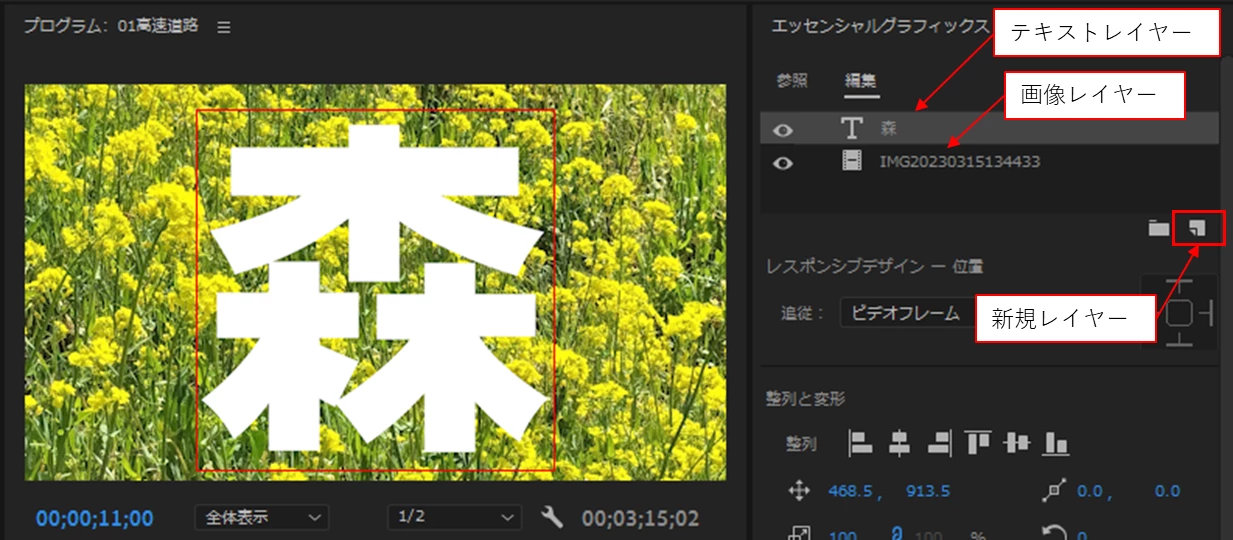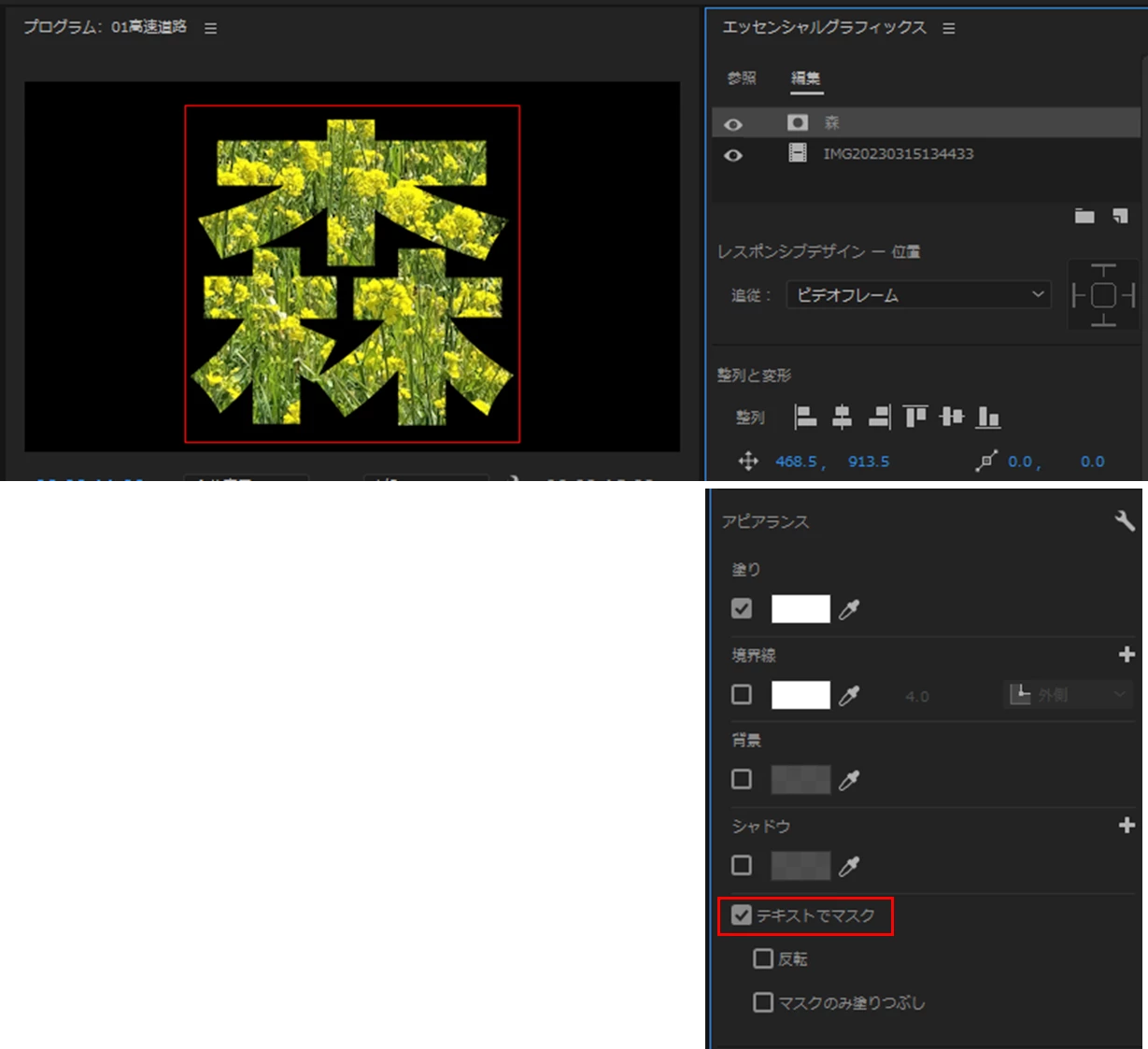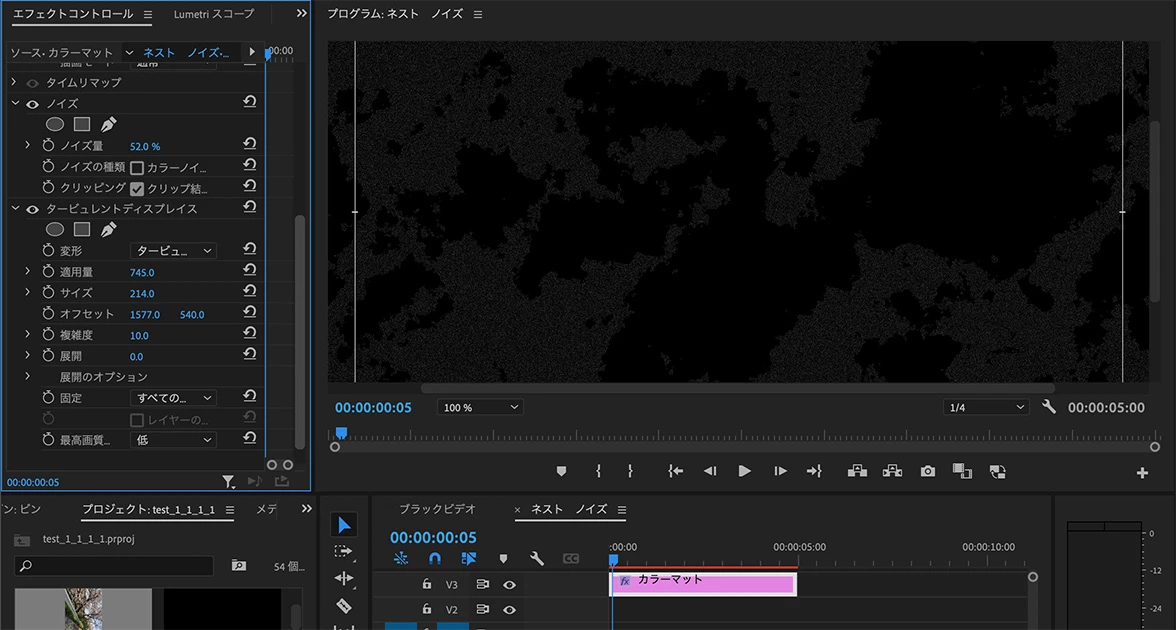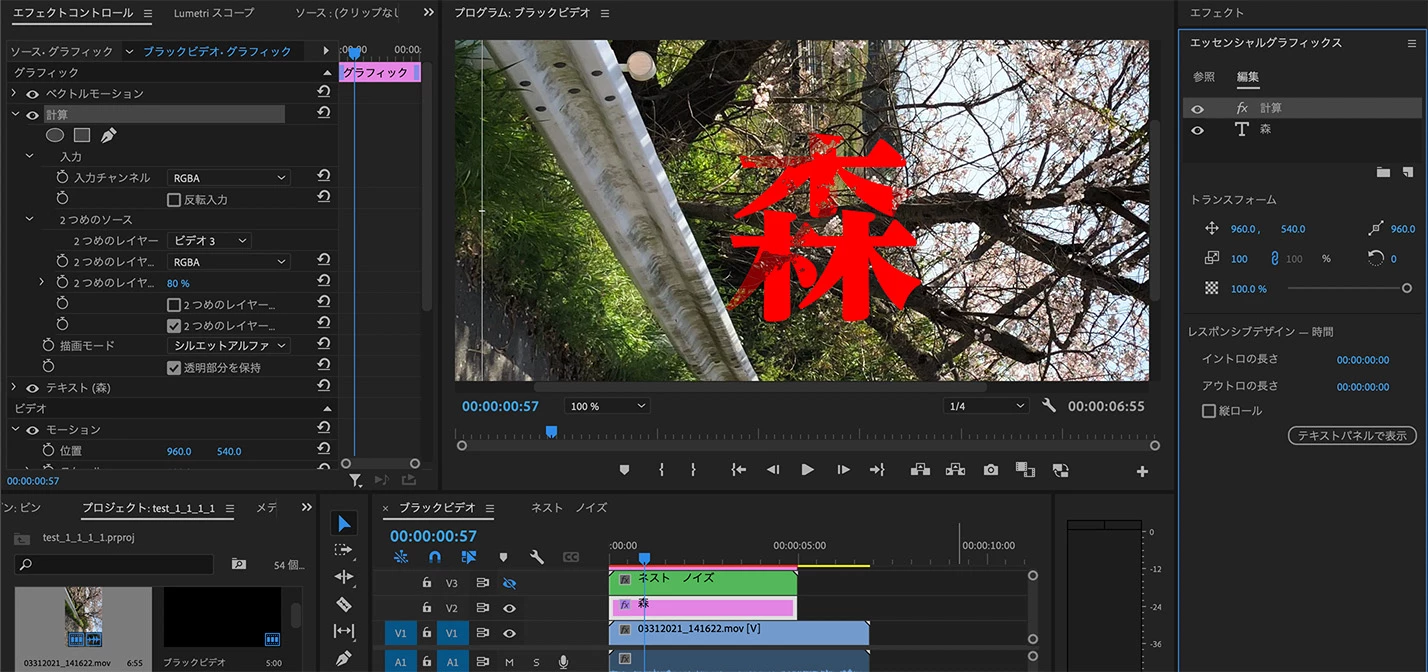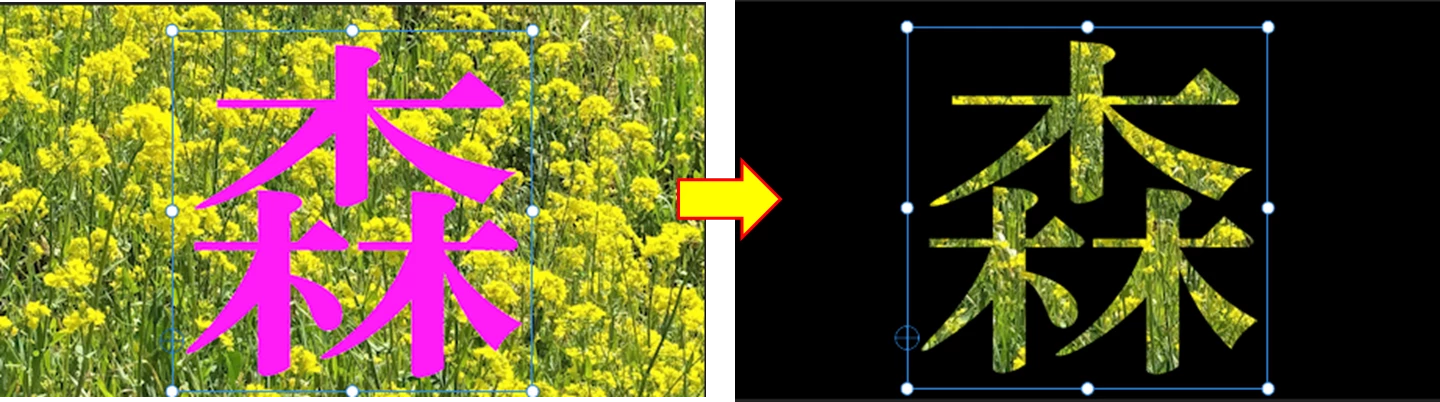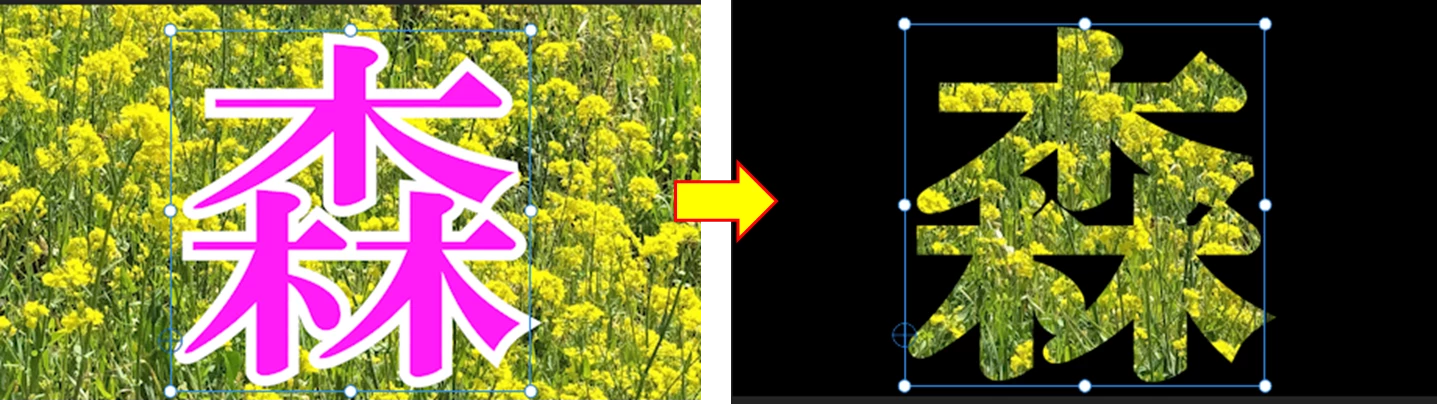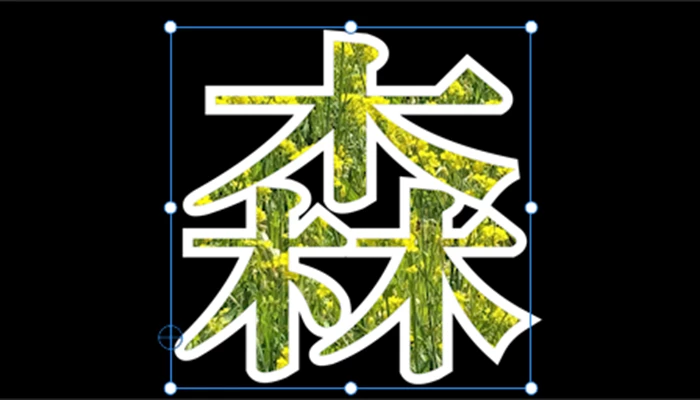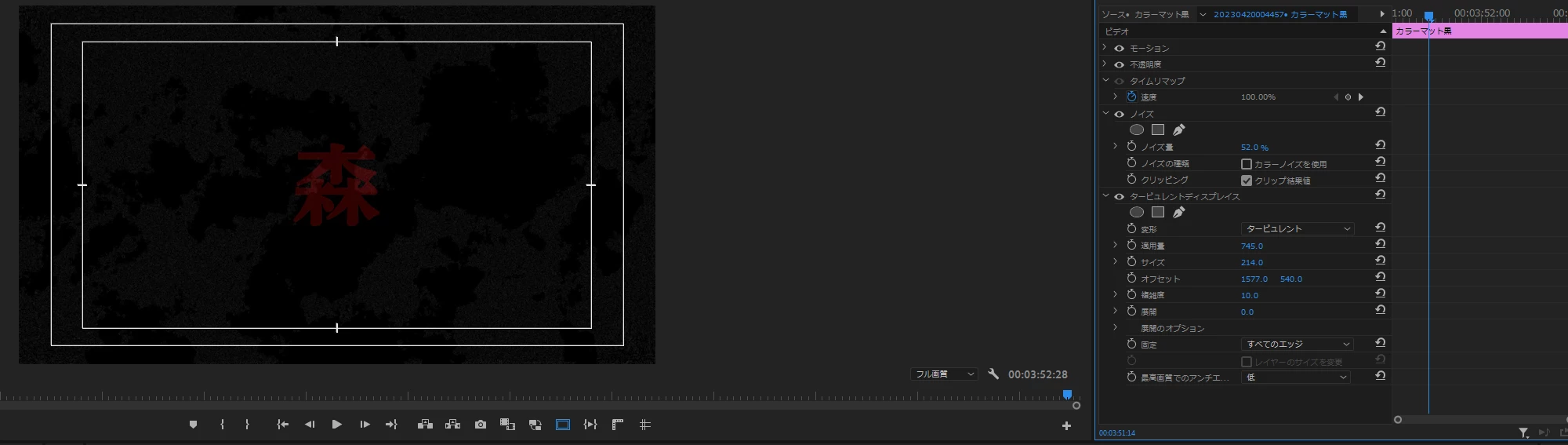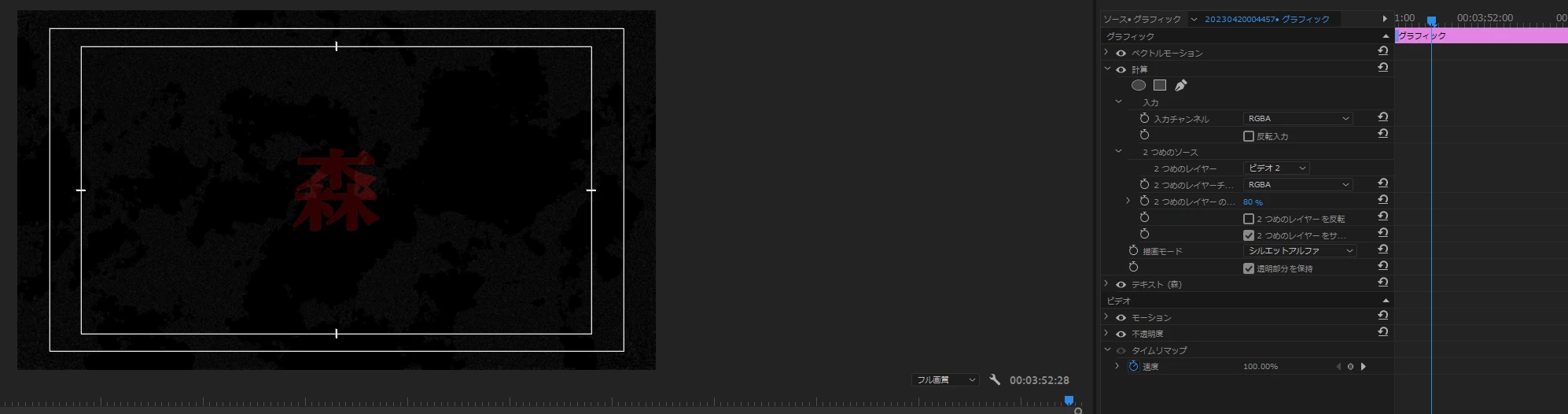
フォントの中に模様
質問です。画像のようにフォントの中に模様?がありますが、作り方を教えて下さい。それと画面にノイズがあると思うのですが、これはエフェクトでしょうか?こちらも作り方分かるでしょうか?よろしくお願い致します。
「スプラッシュ」画像などのキーワードで検索すると適当な素材が見つかるかもしれません。
Premiereだけで素材を作成する場合は、下記の方法はどうでしょう。
新規のカラーマットにエフェクト「ノイズ」と「ターピュレントディスプレイス」でテキストに重ねる素材を作成します。
テキストのシーケンスに作成した素材を配置して、テキストにエフェクト「計算」を適用します。
参考画像では、部分的に透過しているので同じように透過させています。
やってみましたが、自分には上級者過ぎて同じようになりません。お手上げです(;_;)情報ありがとうございます。
>画像のようにフォントの中に模様?がありますが、作り方を教えて下さい。
一つの方法として、文字の中にテクスチャー等の別画像を表示させるという方法があります。
①「エッセンシャルグラフィックス」パネルの「編集」タブをクリックし、文字を打ち込むと「テキストレイヤー」が作成されます。極力太い文字が良いです。さらに「ボールド」を適用すると太くなります。
次に、「新規レイヤー」アイコンをクリックして画像ファイル(ここでは菜の花の画像)を読み込み、テキストレイヤーの下側に配置します。
②「アピアランス」項で「テキストでマスク」にチェックを入れると、文字の中に画像が表示されます。
ご提示のような画像はインターネット等で見つけるか、Photoshop等でご自身で作成したらいかがでしょうか。
しかしご提示の画像では、文字の一部に別の画像を被せているようにも見えるし、何か複雑な方法で作成しているかも知れません。
補足ですが、文字が細い場合、より太くする方法です。
文字が細いとマスクも細くなります。
「アピアランス」項で「境界線」にチェックを入れ幅の数値を入力して境界線を設定すると、境界線を含めた範囲がマスクとなり、太くなります。
「アピアランス」項で「マスクのみ塗りつぶし」にチェックを入れると、境界線を残すことができます。